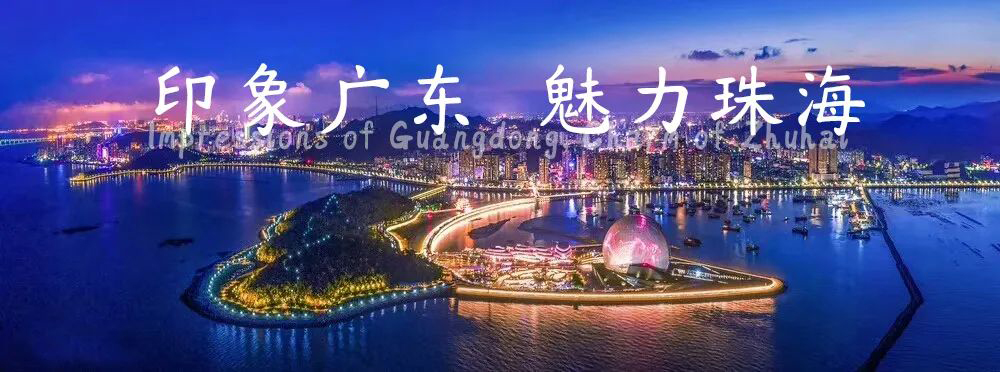
鼎猎珠海体字体信息
鼎猎咨询作为一家珠海本土企业,
希望能创造一套以“珠海”命名的专属字体,以此助力这座浪漫之都、旅游之城,带着珠海特有的文化和故事,传播得更远、更广。让更多的朋友来珠海游玩、定居。这套字体姗姗来迟,终于到了发布的时候
“鼎猎珠海体”是一款书写很新颖的字体,字体大方,适合各种设计作品使用!欢迎下载!